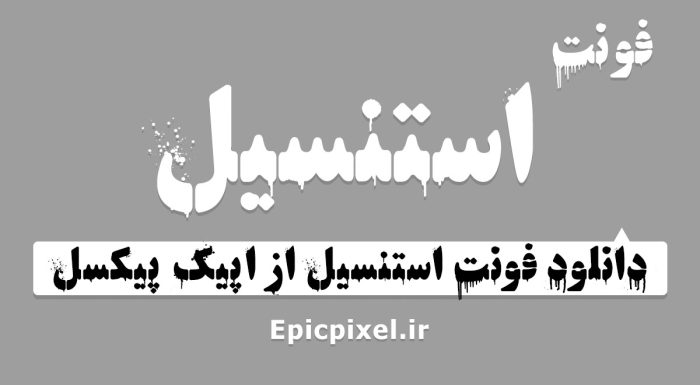
فونت تیتر گرافیتی استنسیل، انتخابی ایده آل برای طراحانی است که به دنبال القای حس نوستالژی و اصالت در آثار خود هستند. این فونت با الهام از هنر گرافیتی و تکنیک استنسیل، حال و هوای خیابان های شهر و پوسترهای قدیمی را به طرح های شما می بخشد. ویژگی بارز این فونت، ساختار منحصربه فرد حروف آن است که با خطوط شکسته و زوایای تند، یادآور نوشته های اسپری شده بر روی دیوارهاست. این ویژگی به طرح شما، چهره ای پویا و جذاب می بخشد و به خوبی می تواند توجه مخاطب را به خود جلب کند.
یکی از مزایای این فونت، ارائه آن در استایل های مختلف است. این تنوع به شما اجازه می دهد تا با توجه به نیاز پروژه، استایل مناسب را انتخاب کنید. به عنوان مثال، استایل «dripped» با افکت چکه کردن رنگ، حس واقعی تری از اسپری را منتقل می کند، در حالی که استایل «old» با بازسازی دقیق حروف استنسیل شده با دست، حس نوستالژی و قدمت را به طرح می بخشد. این فونت همچنین از اعداد فارسی پشتیبانی می کند که برای طراحی های فارسی زبان، امتیازی ویژه محسوب می شود.
البته باید به این نکته نیز اشاره کرد که به دلیل ساختار خاص این فونت، ممکن است برای متن های طولانی و خواندن در اندازه های کوچک، چندان مناسب نباشد. این فونت بیشتر برای عناوین، تیترها، پوسترهای تبلیغاتی و طرح هایی که نیاز به جلوه ای خاص و چشمگیر دارند، توصیه می شود. در واقع، این فونت با ویژگی های خاص خود، به طرح شما شخصیتی متمایز می بخشد و آن را از سایر طرح ها جدا می کند. اگر به دنبال فونتی هستید که بتواند حس اصالت، خلاقیت و انرژی را به مخاطب منتقل کند، فونت تیتر گرافیتی استنسیل گزینه ای عالی برای شماست.
دنیای خلاقانه حروف با دانلود فونت استنسیل
فونت، عنصری کلیدی در طراحی گرافیک است که میتواند پیام و هویت بصری یک اثر را شکل دهد. در میان طیف گستردهای از فونتها، فونتهای استنسیل (Stencil) با ظاهری جسورانه و صنعتی، جایگاه ویژهای دارند. این فونتها که حال و هوای هنر خیابانی و پوسترهای تبلیغاتی دهههای گذشته را تداعی میکنند، به آثار شما چهرهای متمایز میبخشند.
چرا از فونت استنسیل استفاده کنیم؟
دلایل متعددی برای استفاده از فونت استنسیل وجود دارد:
- جلب توجه: خطوط بریده بریده و ضخیم فونتهای استنسیل، به طور طبیعی چشم مخاطب را به خود جلب میکنند و باعث برجسته شدن پیام شما میشوند.
- ایجاد حس نوستالژی: این فونتها با القای حس قدمت و اصالت، برای طراحی پوسترهای مرتبط با رویدادهای تاریخی، موسیقی و فیلمهای قدیمی بسیار مناسب هستند.
- فضای شهری و خیابانی: فونت استنسیل یادآور هنر گرافیتی و دیوارنوشتهها است و میتواند در طراحیهای مرتبط با فرهنگ خیابانی و شهری، کاربرد موثری داشته باشد.
- ایجاد حس قدرت و استحکام: خطوط پهن و محکم این فونتها، القا کنندهی حس قدرت و استحکام هستند و برای طراحی بنرهای تبلیغاتی، بستهبندی محصولات و عناوین قدرتمند، گزینه مناسبی به شمار میروند.
- ایجاد تنوع و پویایی: با ترکیب فونت استنسیل با فونتهای دیگر، میتوانید به طرحهای خود، پویایی و تنوع ببخشید.
انواع فونت استنسیل
در دنیای فونتهای استنسیل، با طیف گستردهای از انواع مختلف روبرو هستیم که هر کدام ویژگیهای منحصربهفردی دارند. برخی از محبوبترین انواع فونت استنسیل عبارتند از:
دانلود- فونتهای استنسیل ساده: این فونتها دارای خطوط بریده بریده و ضخیم هستند و ظاهری تمیز و خوانا دارند.
- فونتهای استنسیل سایهدار: در این نوع فونت، سایهای در پشت حروف قرار میگیرد که باعث ایجاد عمق و بعد در متن میشود.
- فونتهای استنسیل فرسوده: این فونتها با شبیهسازی به حروف کهنه و رنگورفته، حس قدمت و اصالت را به طرح القا میکنند.
- فونتهای استنسیل چندخطی: در این نوع فونت، حروف از چند لایه تشکیل شدهاند که باعث ایجاد افکتهای متفاوتی میشود.
کجا از فونت استنسیل استفاده کنیم؟
با توجه به ویژگیهای ذکر شده، فونتهای استنسیل کاربردهای متنوعی در طراحی گرافیک دارند. برخی از این موارد عبارتند از:
- پوستر و تراکت: با استفاده از فونت استنسیل میتوانید پوسترهای تبلیغاتی و تراکتهای اطلاعرسانی جذاب و تاثیرگذاری طراحی کنید.
- بستهبندی محصولات: فونت استنسیل میتواند به بستهبندی محصولات شما، ظاهری خاص و متمایز ببخشد، به ویژه برای برندهای مرتبط با حوزههای ورزشی، موسیقی و مد.
- عناوین و تیترها: با استفاده از فونت استنسیل برای عناوین و تیترها، میتوانید توجه مخاطب را به بخشهای مهم متن جلب کنید.
- طراحی وبسایت و اپلیکیشن: استفادهی بهجا از فونت استنسیل در طراحی وبسایت و اپلیکیشن میتواند به ایجاد فضایی پویا و متمایز کمک کند.
- تیشرت و لباس: فونت استنسیل با القای حس شهری و خیابانی، برای طراحی روی تیشرت و لباسهای کژوال، بسیار مناسب است.
استفاده از فونتهای استنسیل در وبسایت، باید با احتیاط انجام شود. به دلیل ضخامت و خطوط بریده بریده، ممکن است این فونتها در سایزهای کوچک خوانایی خود را از دست بدهند.